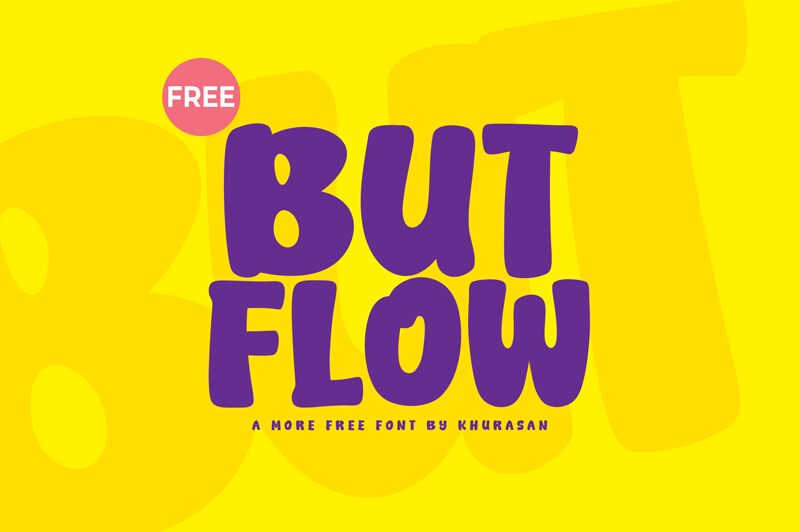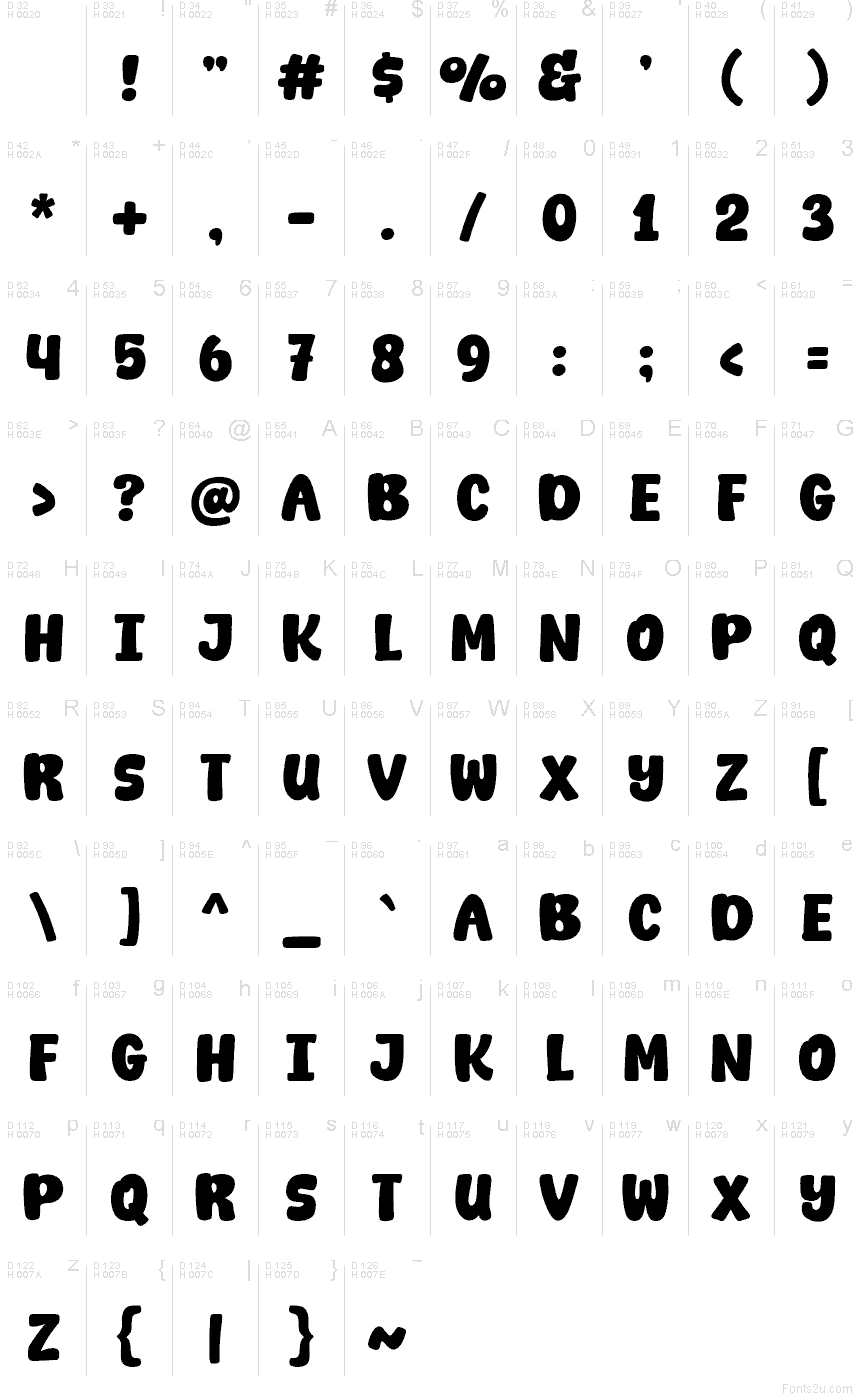
Butflow od Khurasan je bezplatný, robustní kreslený font, který zaujme svými měkkými, nepravidelnými tvary a hravým rytmem připomínajícím ruční vyřezávání. Písmena působí široce a živě; mají zaoblené rohy, jemně nepravidelné okraje a sevřené tvary, které dodávají slovům výrazný a přátelský vzhled.
Tento font zdarma je ideální pro obálky dětských knih, obaly na snacky, branding hraček, plakáty na párty, komiksové nadpisy a animované úvodní titulky. Nejlépe vynikne v krátkých nadpisech a titulcích, kde mají nadrozměrné tvary a volné rozestupy prostor pro dokreslení designu.
Prezentace a vizuální ukázka písma Butflow
Mapa znaků písma Butflow
Mapa znaků písma Butflow: Základní latinka, strana 1
Glyfy písma Butflow — Základní latinka, strana 1